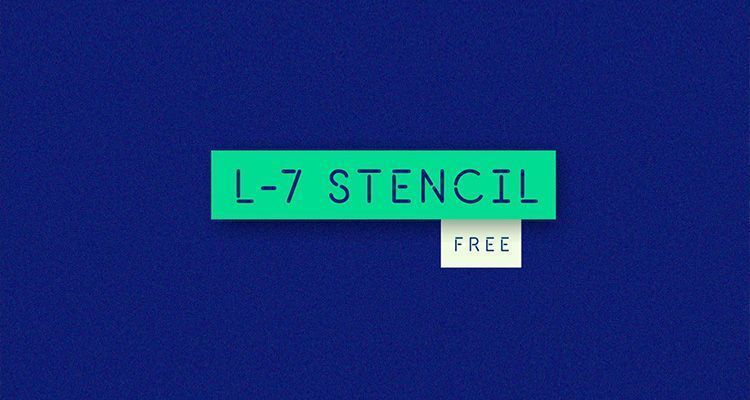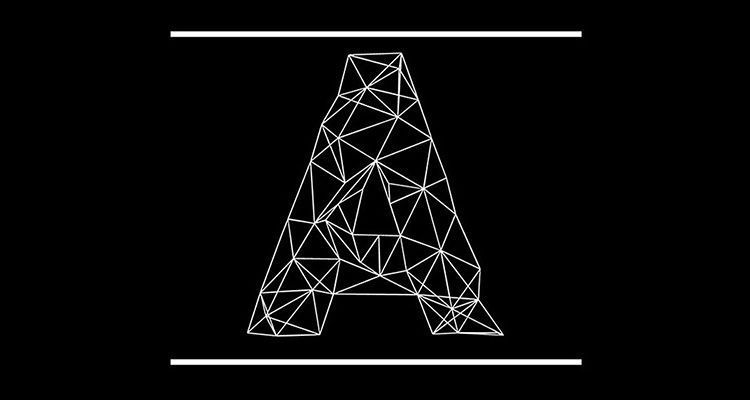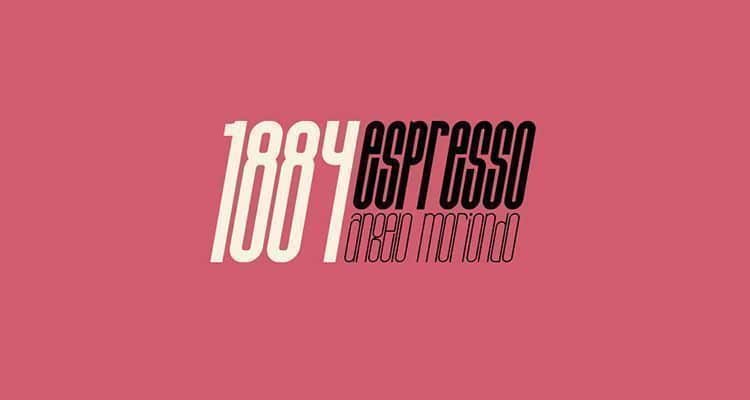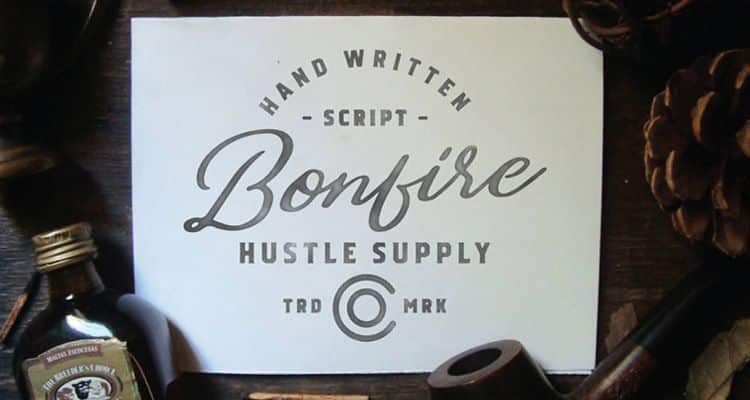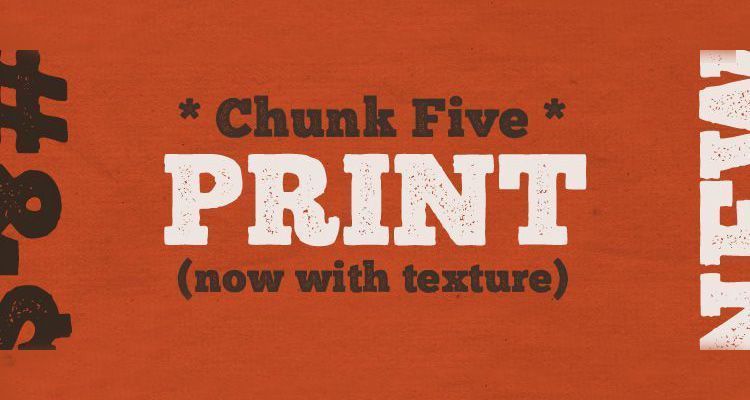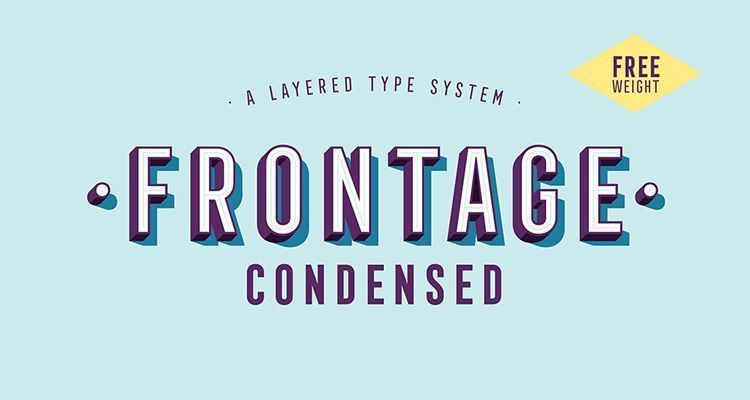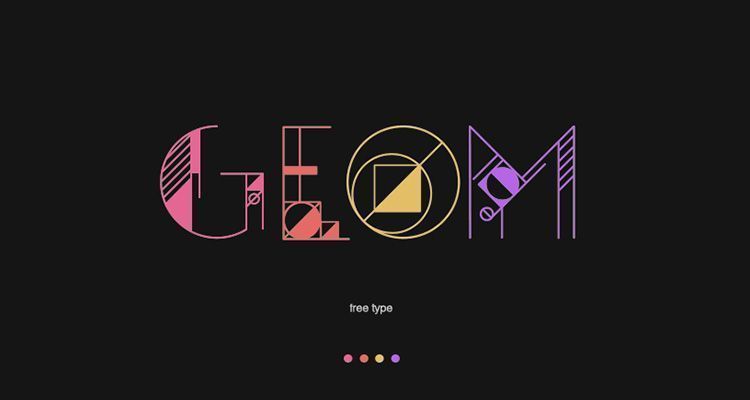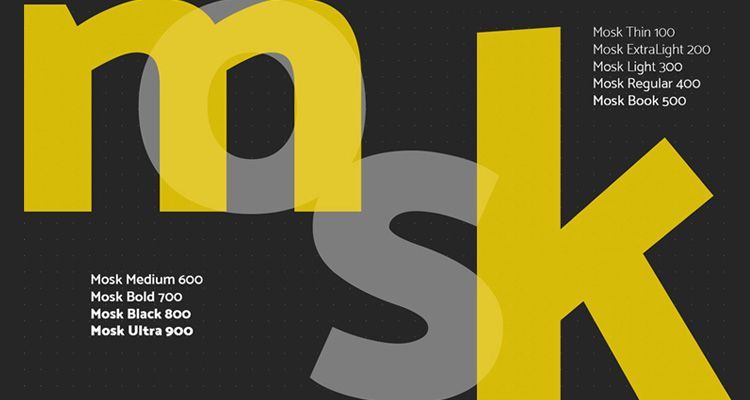
Una fantástica selección con las diez mejores tipografías gratuitas
Cada vez más, los diseñadores diseñan y ponen sus trabajos a disposición de todo el mundo. Gracias a la globalización son más los profesionales que deciden compartir sus creaciones con la comunidad y así buscar su propio camino en el competido mundo del diseño.
Y es que la tipografía ha cambiado mucho desde que hace 60 años Max Miedinger inventara la Helvetica, o Adrian Frutiger hiciera lo mismo con la tipografía Futura. Anteriormente, la falta de opciones llevaba a los profesionales del diseño a inventarse sus propias tipografías para poder proyectar sus ideas en papel. La aparición de los ordenadores y su normalización en las oficinas hizo desaparecer las linotipias de las imprentas, empujadas por las nuevas tecnologías en composición de textos.
La irrupción de internet y, como consecuencia, la globalización y la democratización del diseño nos ha llevado al extremo opuesto. La facilidad para pensar, crear y compartir ha saturado la red de tipografías. Esto ha llevado a los diseñadores actuales a trabajar con pocas tipografías para no perder tiempo buscando entre tantas opciones. Prueba de ello son las diez mejores más utilizadas por los diseñadores o las diez mejores tipografías utilizadas en diseño web.
Walkon
Tipografía Walkon Gratuita
En primer lugar, WalkOn es una tipografía creada originalmente para el diseño de una marca de moda. Sus creadores son Hanson Chan y el equipo de Frames y está inspirada en la el Art Decó y Nouveau, con un enfoque contemporáneo. Puedes conseguir la tipografía WalkOn gratuitamente tan solo enviándole un email solicitándola a su autor: email Chan.
BonFire
Tipografía Bonfire Gratuita
En Charlottetown, Canadá, encontramos este trabajo de Jeremy Vessey (Hustle Supply Co.). Bonfire es una gran fuente dibujada mano y a pincel. Se presenta con 2 juegos de letras mayúsculas y está equipada con unos pocos caracteres de minúsculas alternas diferentes, así comos washes y caracteres de Europa occidental. Disponible gratuitamente para uso personal. Descargar Bonfire font.
Bohema
Tipografía Bohema Gratuita
Bohema es el nombre con el que el ilustrador y diseñador portugués João Oliveira ha bautizado a la tipografía más retro de todo su catálogo de diseños tipográficos. Se trata de una tipografía con reminiscencias del Art Deco con un toque moderno. Ideal para aquellos diseños con una estética con evocaciones del pasado. Bohema es perfecta para titulares, para diseños de branding, lettering en diseño editorial y para texto en piezas de merchandising. Está disponible de forma gratuita en su versión demo. Descargar Bohema font.
Mosk
Tipografía Mosk Gratuita
El diseñador rumano Iulian Maftei es el autor de esta tipografía que incluye 9 variantes de grosores. Su calidad técnica es muy aceptable (recordemos que es una fuente gratuita). La familia Mosk va desde un Thin 100 (la más delgada) a una Ultra-bold 900 (la más gruesa). Esta palo seco y de aspecto limpio es muy versátil en cuanto a usos: titulares, logos, identidad corporativa. Solo tiene un ‘pero’, no incluye caracteres especiales, solo caracteres ingleses. Descargar Mosk Typeface.
Frontpage
Tipografía Frontage Gratuita
Desde París, Francia, el diseñador Juri Zaech presenta esta tipografía condensed. Está pensada para web, cartelería y logos. Este set se compone de 5 fuentes + 1 gratuita, que combinan todas entre sí. La gratuita es la de letras perfiladas. Pueden superponerse unas a otras y recuerdan a las luces de neón y carteles de espectáculos. La versión gratuita solo incluye la variante perfilada hueca, siendo las otras 5 de pago. Descargar Frontage font.
Road Free
Tipografía Road Free Gratuita
Patrick Seymour, desde Montreal (Quebec, Canadá) presenta Road Free Font. Esta fuente disponible solo en caja alta tiene la particularidad de simular las líneas de los neumáticos. Mencionar que esta fuente no es una tipografía instalable, sino que viene en un archivo de Illustrator. De esta forma, hay que hacer un trabajo de composición, una a una, para formar las palabras. Descargar Road Free font.
GEOM
Tipografía Geom Gratuita
GEOM es la tipografía display diseñada por el diseñador y director de arte brasileño Danilo Gusmão Silveira. Es una tipografía decorativa, compuesta por caracteres en caja alta e inspirada en las líneas y formas del universo de la geometría: líneas rectas, curvas, ángulos, planos, círculos, circunferencias, triángulos, cuadrados, etc. Carece de remates pero está llena de elementos decorativos. Esta tipografía gratuita resulta ideal para la creación de carteles, flyers, portadas de discos, merchandising, piezas animadas en motion graphics o, incluso, para realizar experimentos tipográficos. Descargar GEOM font.
Chunk
Tipografía Chunk Gratuita
Chunk es una tipografía slab-serif ultra bold, especialmente ideada para potentes titulares. Se trata de una tipografía para captar la atención del lector desde que le echa el ojo al titular. Fue creada en el 2009 por la diseñadora californiana Meredith Mandel, quien se inspiró en la estética del western, en las tipografías y en el sistema de impresión que se empleaba para crear los titulares de los periódicos del Antiguo Oeste americano. Descargar Chunk Font.
L-7 Stencil Free
Tipografía L7 Stencil Gratuita
Creada por Luis Calzadilla desde Barquisimeto, Venezuela, esta tipografía es útil para logos y titulares, ya que carece de minúsculas. Aunque incluye la letra Ñ, aunque no tiene tildes, de forma que puede servir para crear palabras sueltas. Disponible gratuitamente para todo tipo de usos. Si bien, su creador solicita recibir muestras del trabajo realizado con ella y citar en los créditos en el caso de que se use con motivos comerciales. Descargar L7 Stencil Font.
Adamas Regular
Tipografía Adamas Gratuita
Y para acabar, la Adamas está diseñada por Octavian Belintan, diseñador gráfico del estudio Colorblind con base en Bucarest (Rumanía). Esta tipografía –solo disponible en caja alta– puede que no encaje en la descripción de ‘tipografía legible’, pero sin duda es una buena candidata para jugar y experimentar con ella. Descargar Adamas Font.